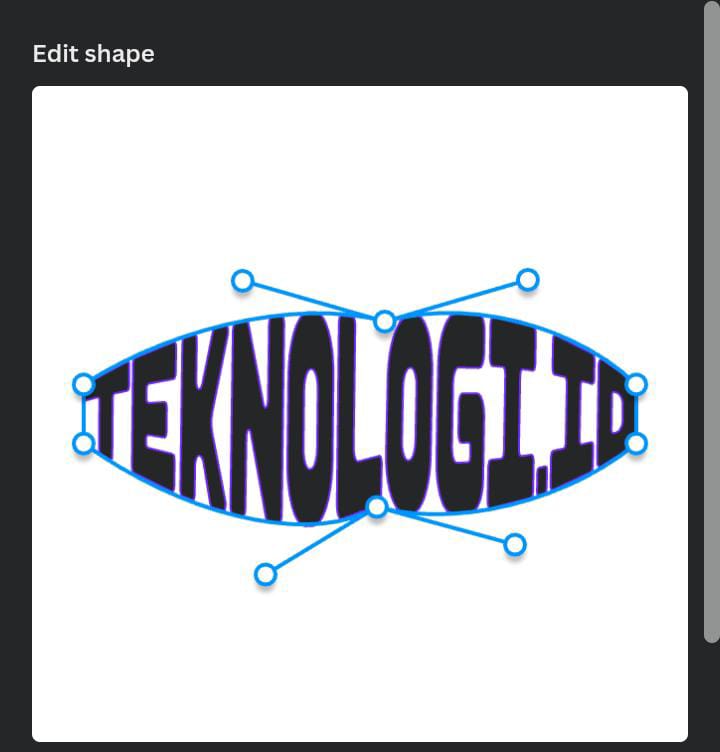
menjadi suatu kebutuhan sebagai sarana menyampaikan informasi, mem-branding
diri atau produk & jasa, dan banyak hal lainnya. Namun, masih banyak yang
belum tahu cara agar membuat konten yang lebih menarik. Salah satu cara untuk
membuat konten yang kita buat menjadi lebih menarik adalah dengan menggunakan
tipografi.
Dilansir dari artikel Career
Foundry, Tipografi adalah seni menyusun huruf dan teks agar tulisannya mudah
dibaca, jelas, dan menarik secara visual bagi pembaca. Hal tersebut melibatkan
gaya, penampilan, dan struktur font, yang bertujuan untuk menimbulkan emosi
tertentu dan menyampaikan pesan-pesan khusus. Singkatnya, tipografi adalah yang
membuat teks menjadi hidup.
Dengan aplikasi yang memiliki akses serta fitur-fitur mudah, Canva, kamu kini bisa mengkreasikan tipografi sendiri. Berikut beberapa tips dan trik serta rekomendasi font untuk membuat kontenmu jadi lebih menarik!
Membuat Tipografi di Canva
Ada beberapa hal yang harus dilakukan
saat Anda ingin membuat tipografi dalam konten Anda. Yang pertama adalah
audiens, jika konten yang akan Anda buat memiliki audiens anak-anak, maka tipografi
yang cocok adalah yang menggemaskan dan menggunakan warna mencolok. Contohnya
adalah tipografi berikut:
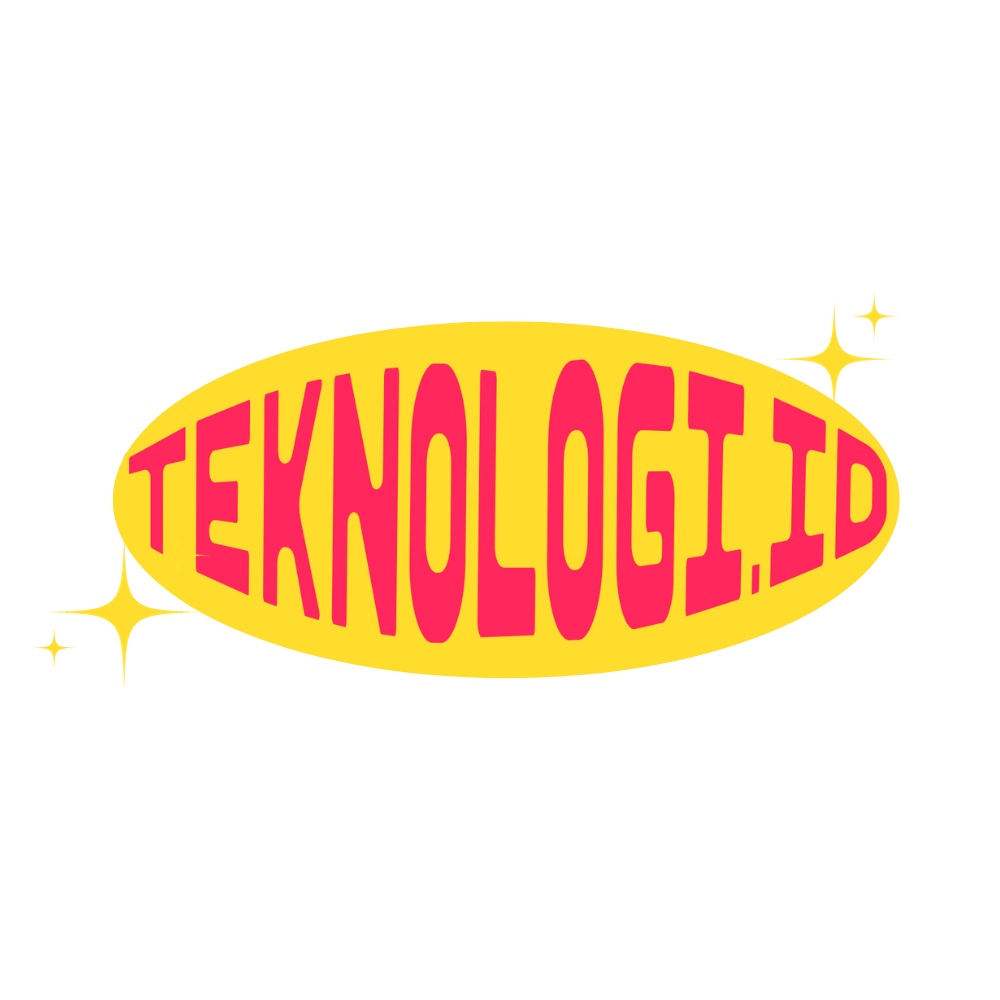
Font yang digunakan:
Chido 123
Tipografi di atas dapat kamu kreasikan sesuka-mu bentuk dan warna-nya. Simak cara-nya berikut:
Pertama, buka aplikasi Canva, lalu klik “Buat Desain” atau tanda +. Pilih ukuran kanvas yang kamu butuhkan.
Setelahnya, Klik kembali tanda + yang berada di pojok kiri layar Anda. Geser toolbar yang ada di bawah hingga menemukan “Aplikasi” atau “Apps”.
Selanjutnya, pada kolom search ketik “TypeCraft” dan klik “Open”
Langkah berikutnya, Anda memilih font yang berada di menu aplikasi tersebut.
Lalu, ubah teks sesuai dengan teks yang Anda inginkan
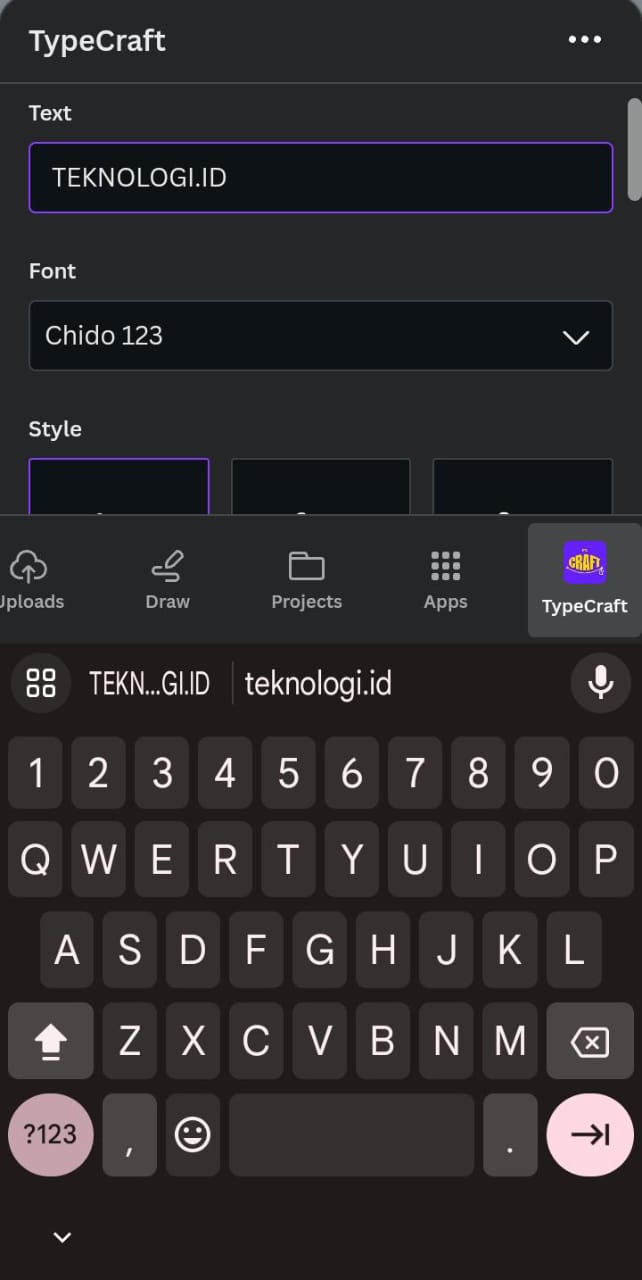
Skrol ke bawah, Anda akan menemukan kolom “Edit Shape”
Untuk mendapatkan bentuk
seperti contoh di atas, Anda hanya perlu menarik bagian tengah shape text tersebut
ke atas untuk bagian atas text, dan ke bawah untuk bagian bawah text.
Selain itu, Anda juga dapat menambahkan dan mengganti warna outline agar tipografi Anda lebih menarik lagi. Warna teks pun bisa diubah sesuka Anda
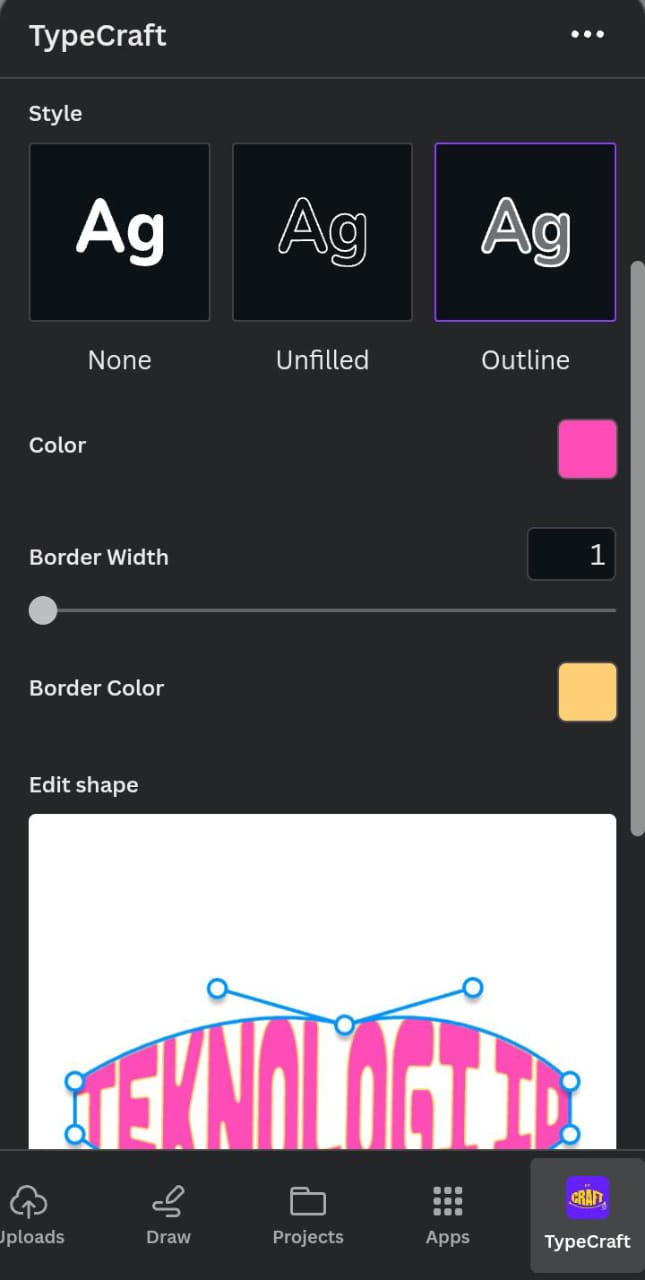
Jika sudah, Anda tinggal
meng-klik “Add to element” dan voila! Tipografi Anda sudah selesai.
Untuk menambah kesan lucu,
tambahkan juga elemen-elemen yang telah disediakan Canva.
TypeCraft bisa
dimanfaatkan untuk membuat bentuk tipografi sesuai selera Anda secara gratis
dan tanpa ribet. Selain TypeCraft, Anda juga bisa memanfaatkan font-font gratis yang tersedia di Canva agar konten buatan Anda semakin menarik. Berikut beberapa rekomendasi font yang bisa Anda gunakan untuk mempercantik konten Anda!
Rekomendasi Font Canva
Font Retro:
Nectarine
Gliker Semibold
Bogart Black
Adam Script Heavy
Berkshire Swash
Genty
Font Aesthetic
Rochester Twee
New Romantic
Aubrey
Bohemian Soul
Rumble Brave
Margin
Sunshine Display
Kare Gradient
Loubag
Barbra
Tan Astoria
Pinyon Script
Font Cute:
DM Bubble Pop
Spiro
Coola Regular
Lazy Dog
More Sugar
Pagkaki
Hitchcut
Laries (Script)
Marykate
Aprila Bold
Font Tema Horror:
Charu Chandan Blood DAI
ABYS
SAVAGE
JEEPERS
ALLEGREYA SC